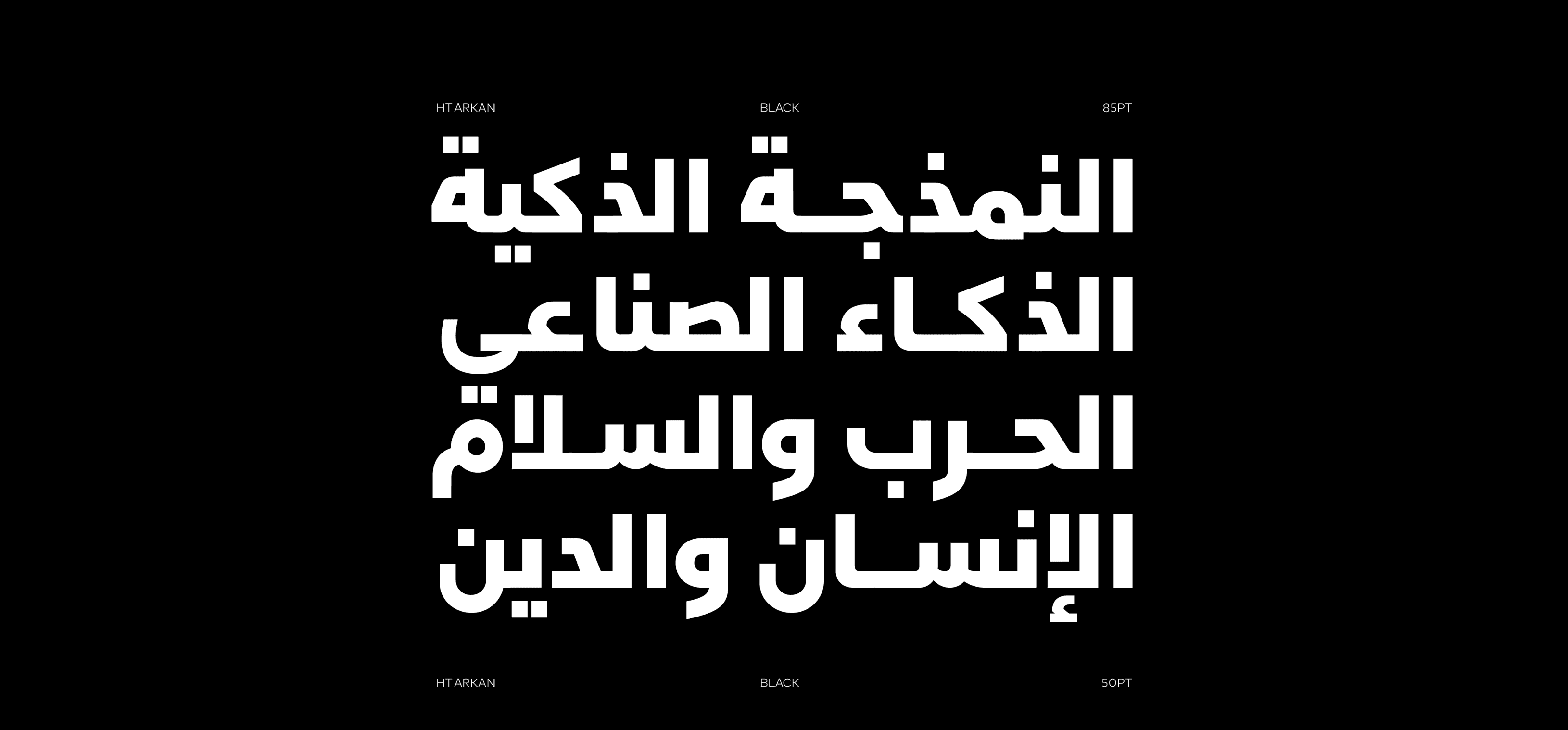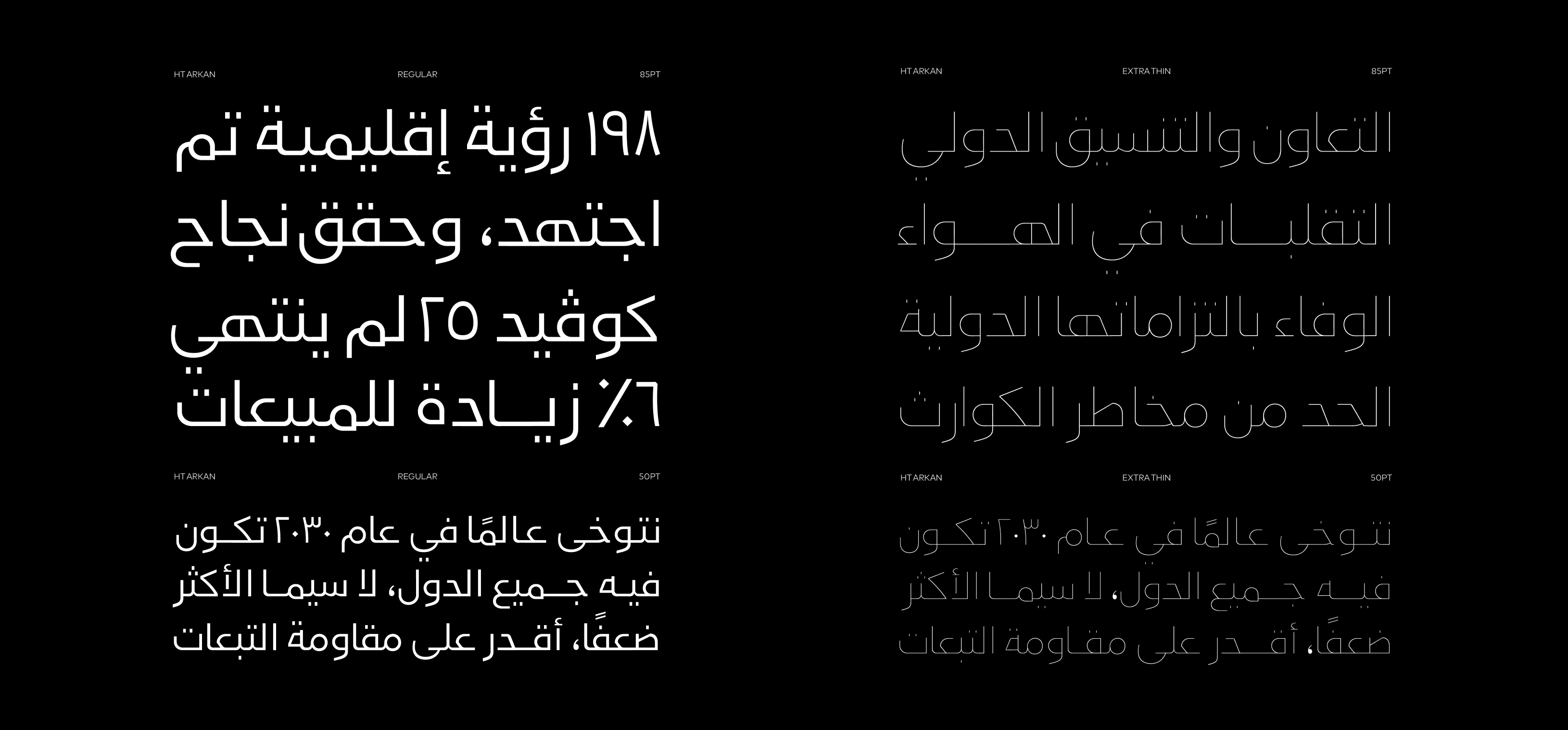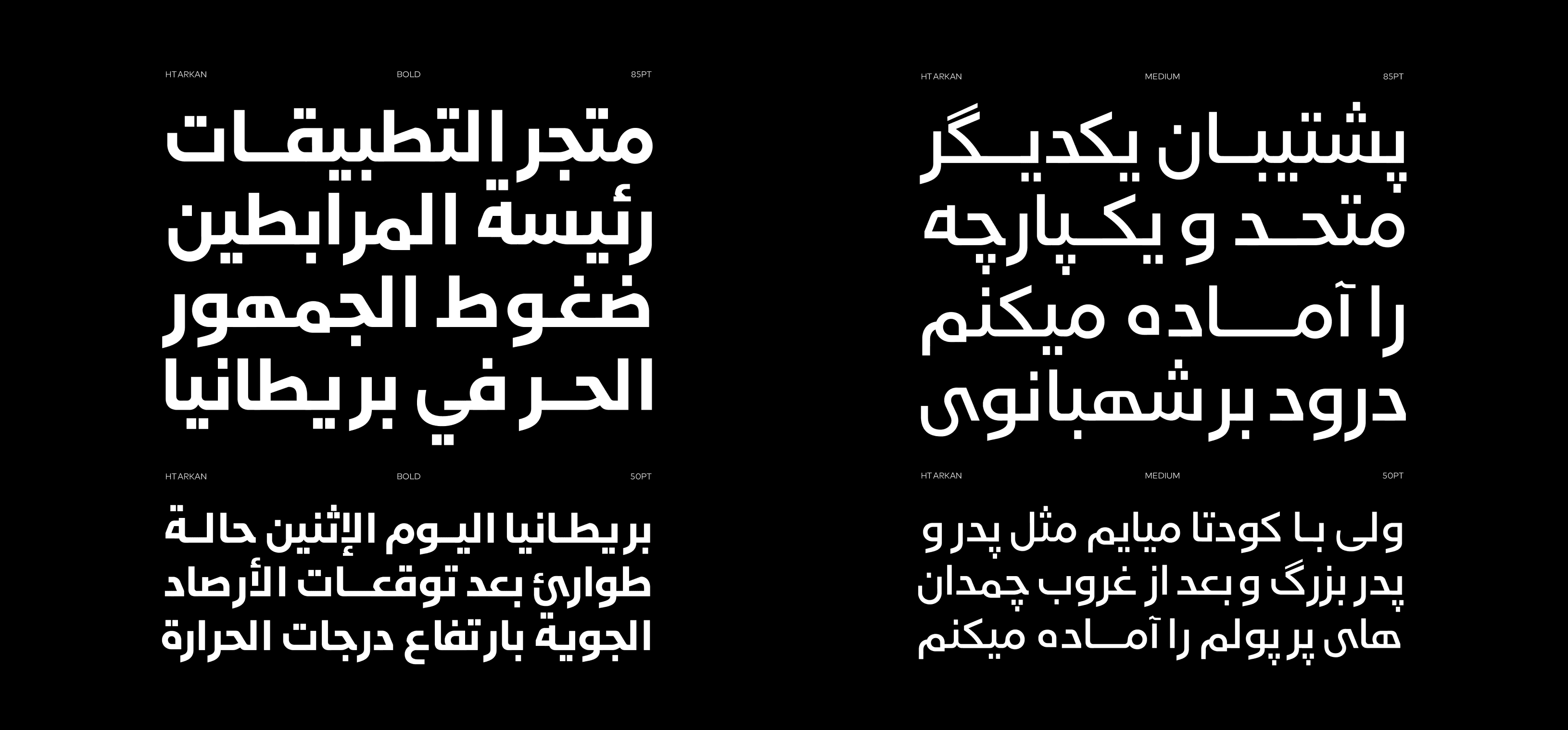
خط أركان – HT Arkan
خط عربي مخصص للهوية البصرية، من تصميم محمد هادي، يجمع بين أسلوبي النسخ والكوفي بانسجام بصري معاصر.
تتكوّن عائلته من تسعة أوزان تبدأ من Hairline حتى Ultra Black، ما يمنحه مرونة عالية في الاستخدام عبر مختلف تطبيقات التصميم.
مثالي للعناوين، واجهات الاستخدام، الإعلانات، والتصميمات التجارية، ويتميز بطابع عصري وودود يعكس الاحترافية والحداثة.